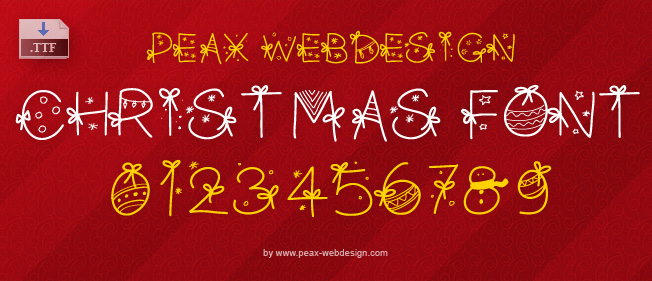
PW Christmas font | 11 décembre 2012 - Gratuit pour usage personnel
Voici un exemple d'utilisation de la police de caractères PW Christmas font, spécialement créée pour les fêtes de fin d'année, Noël ou le nouvel an. Mais rien ne vous empêche de l'utiliser pour un anniversaire ou pour toute autre occasion.